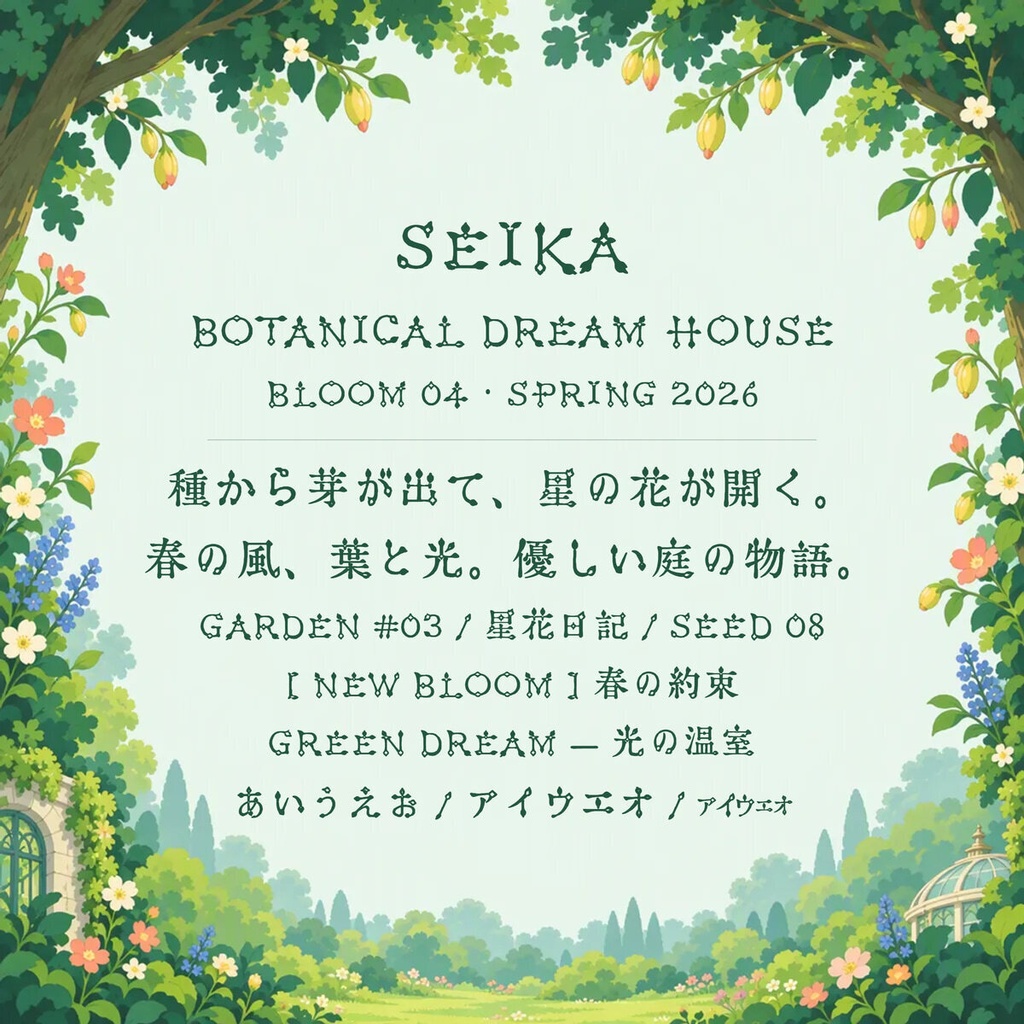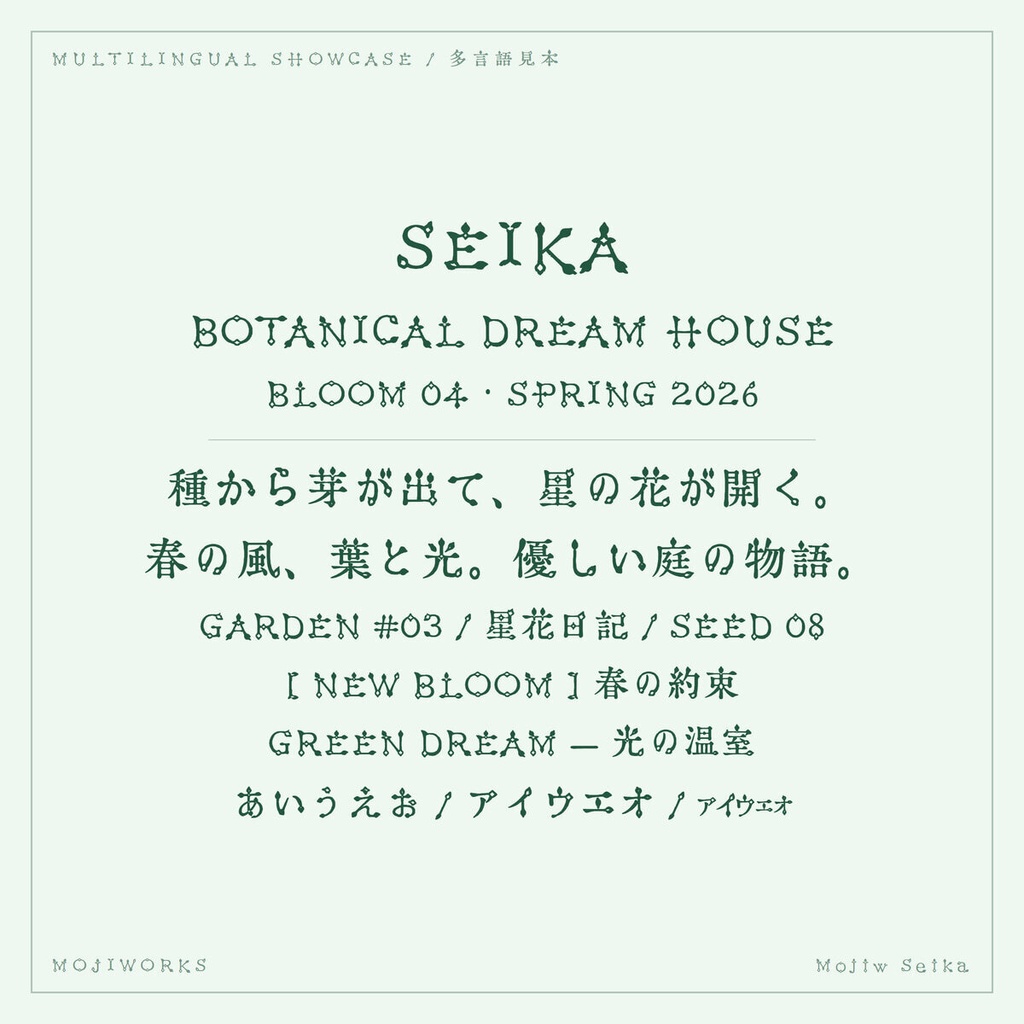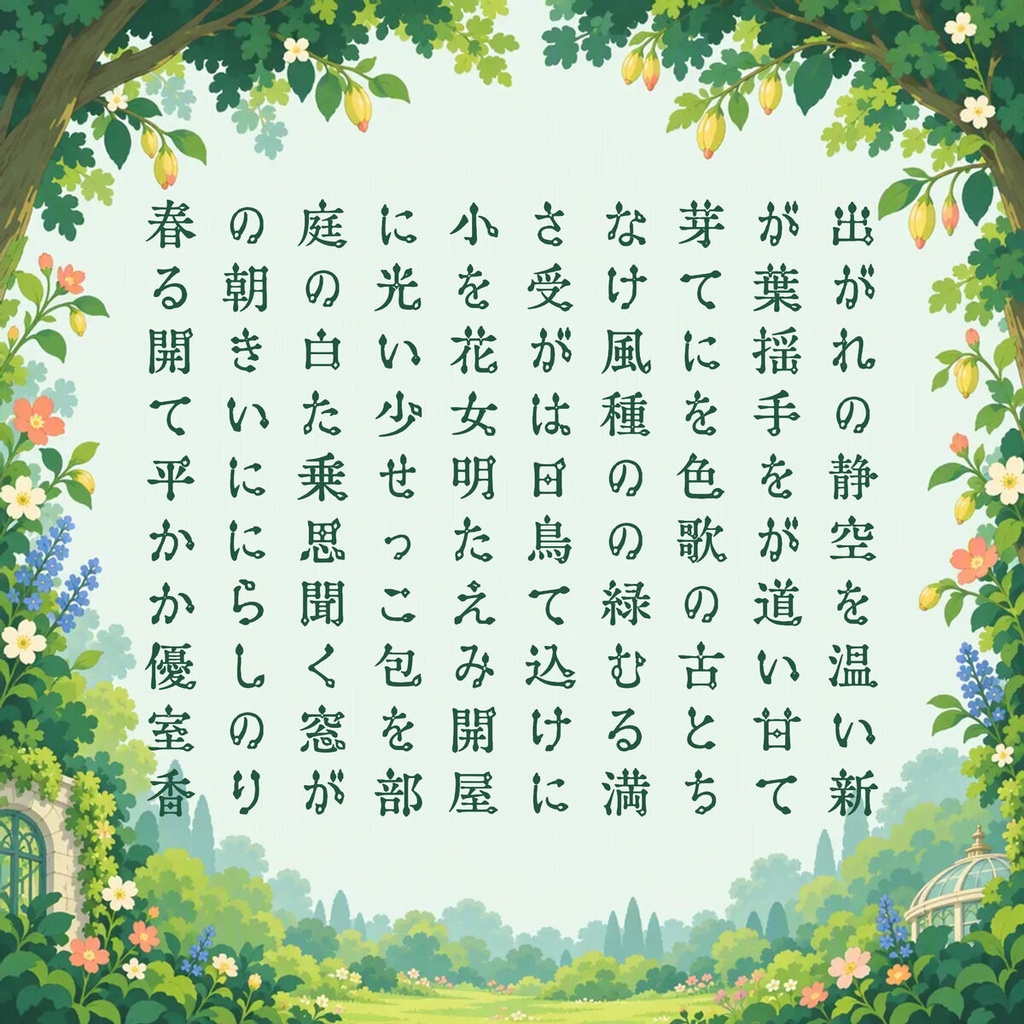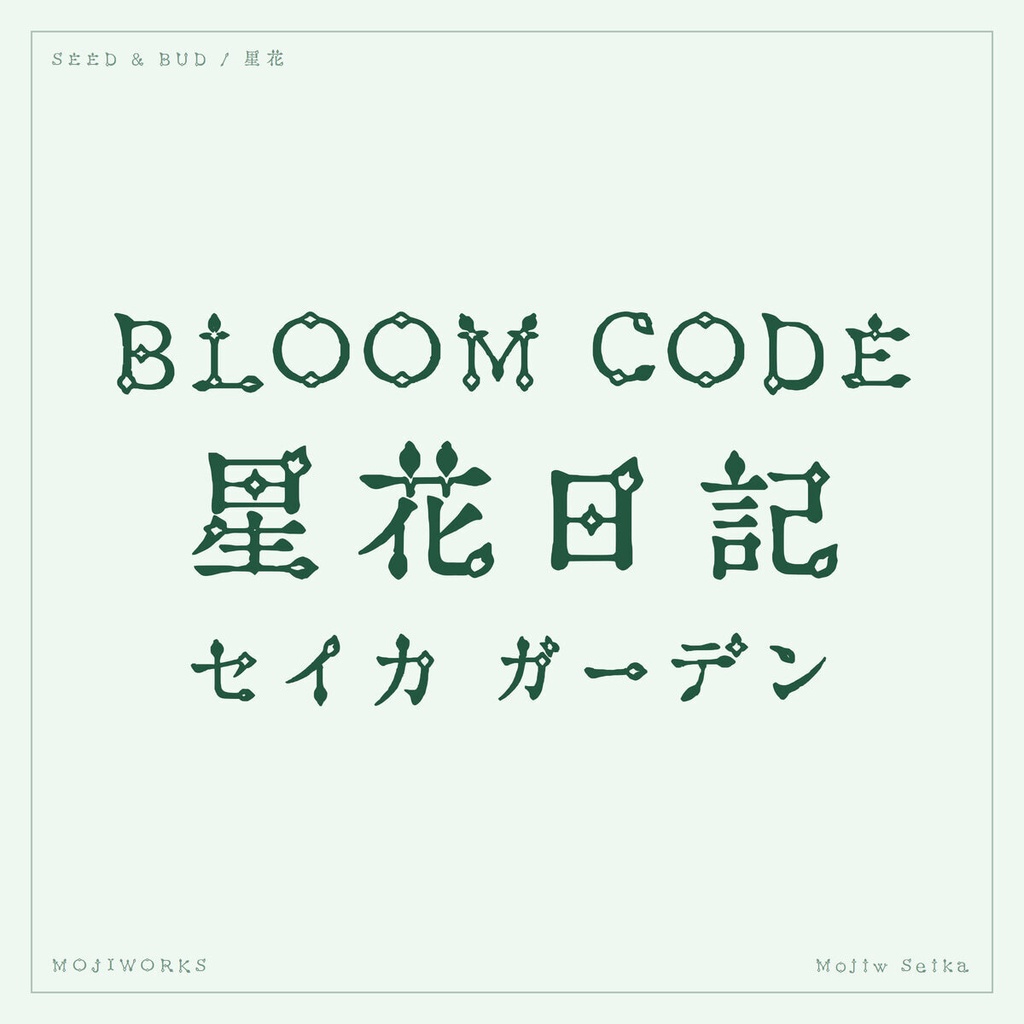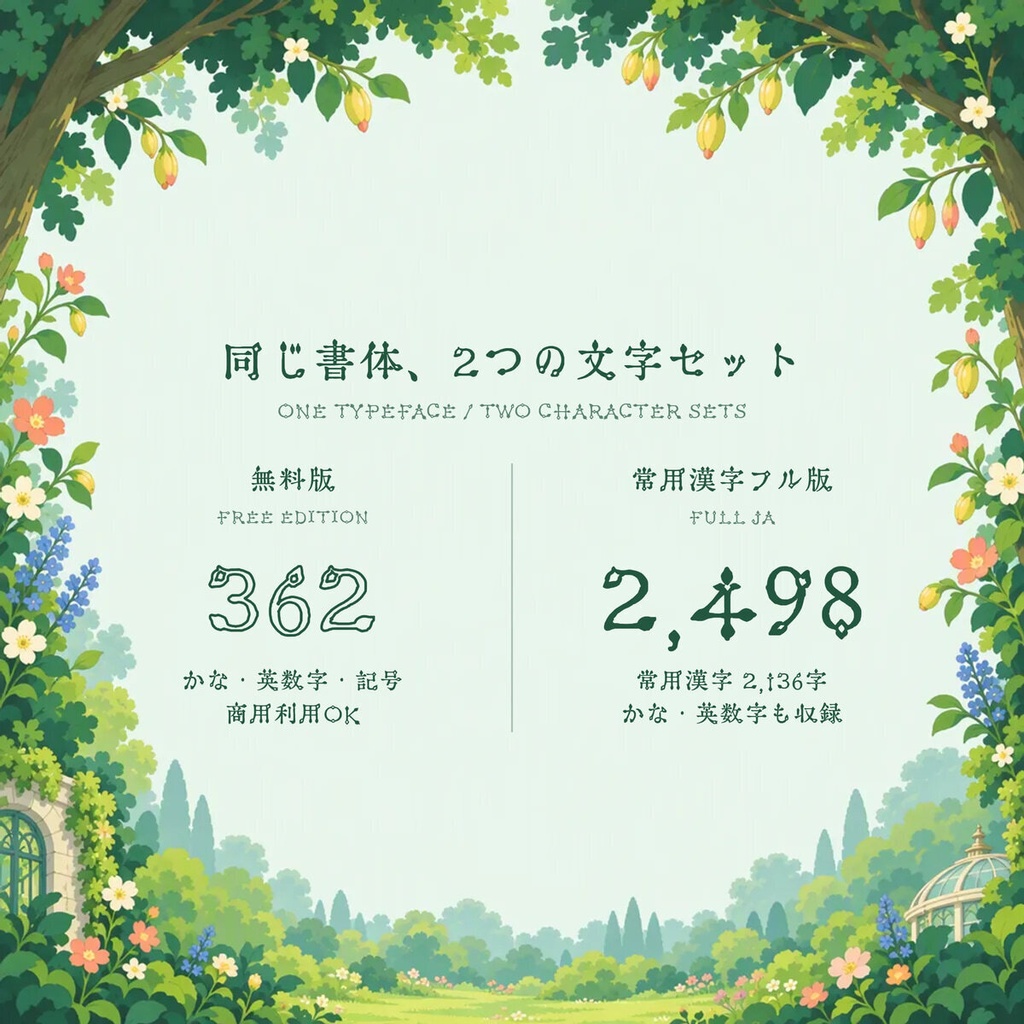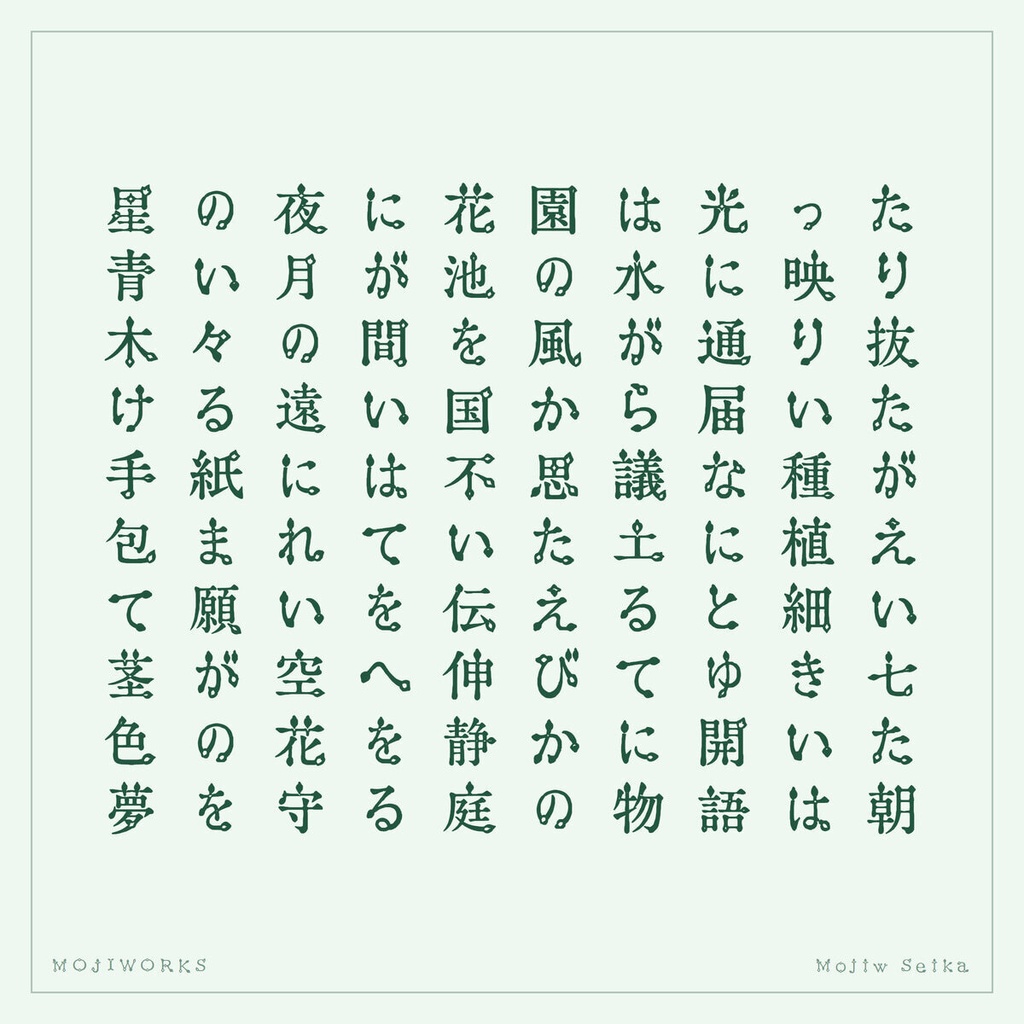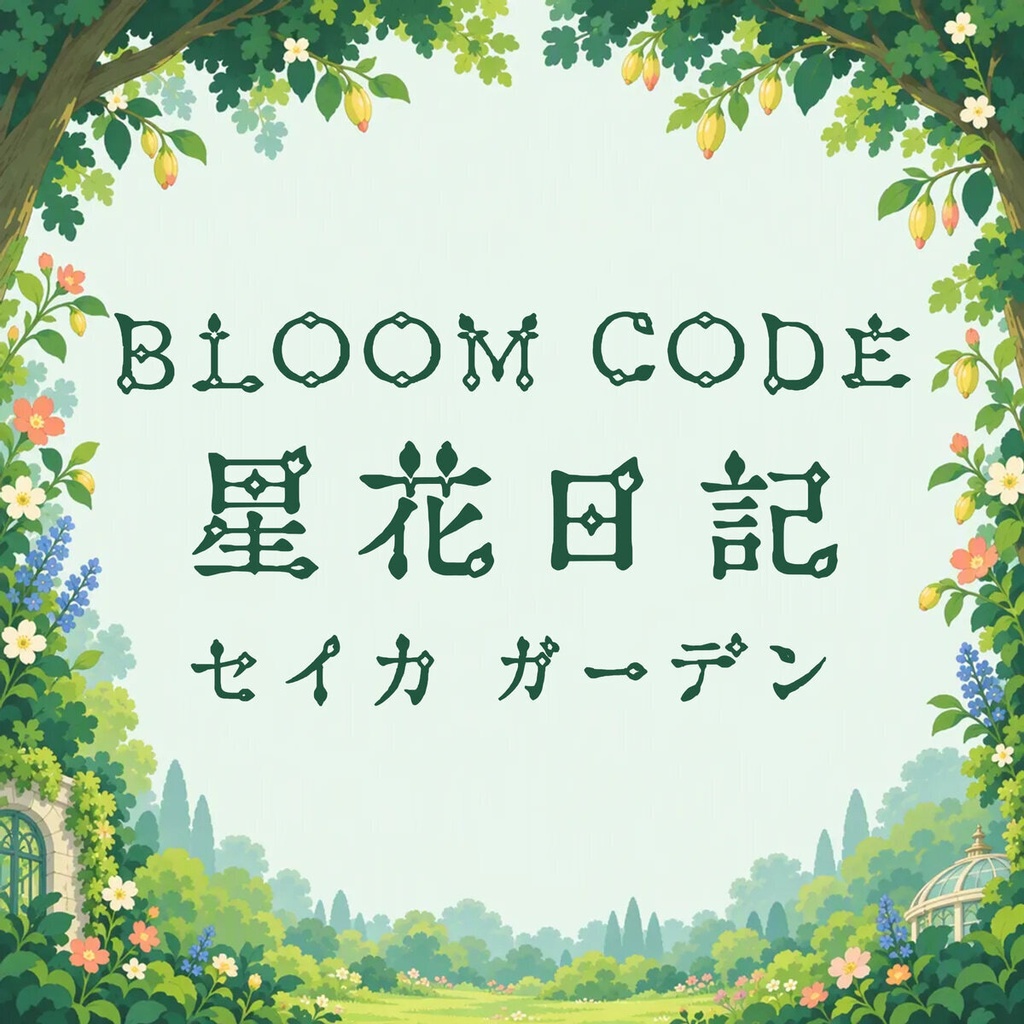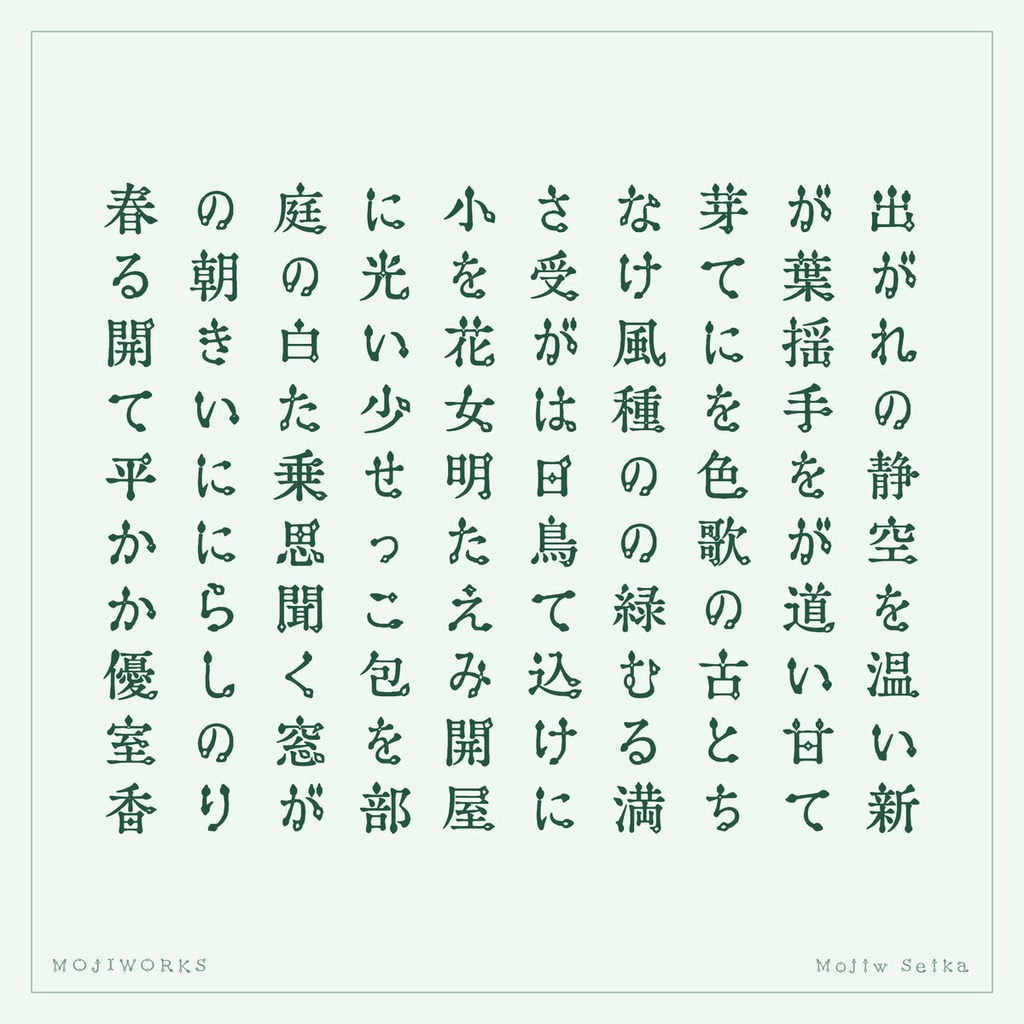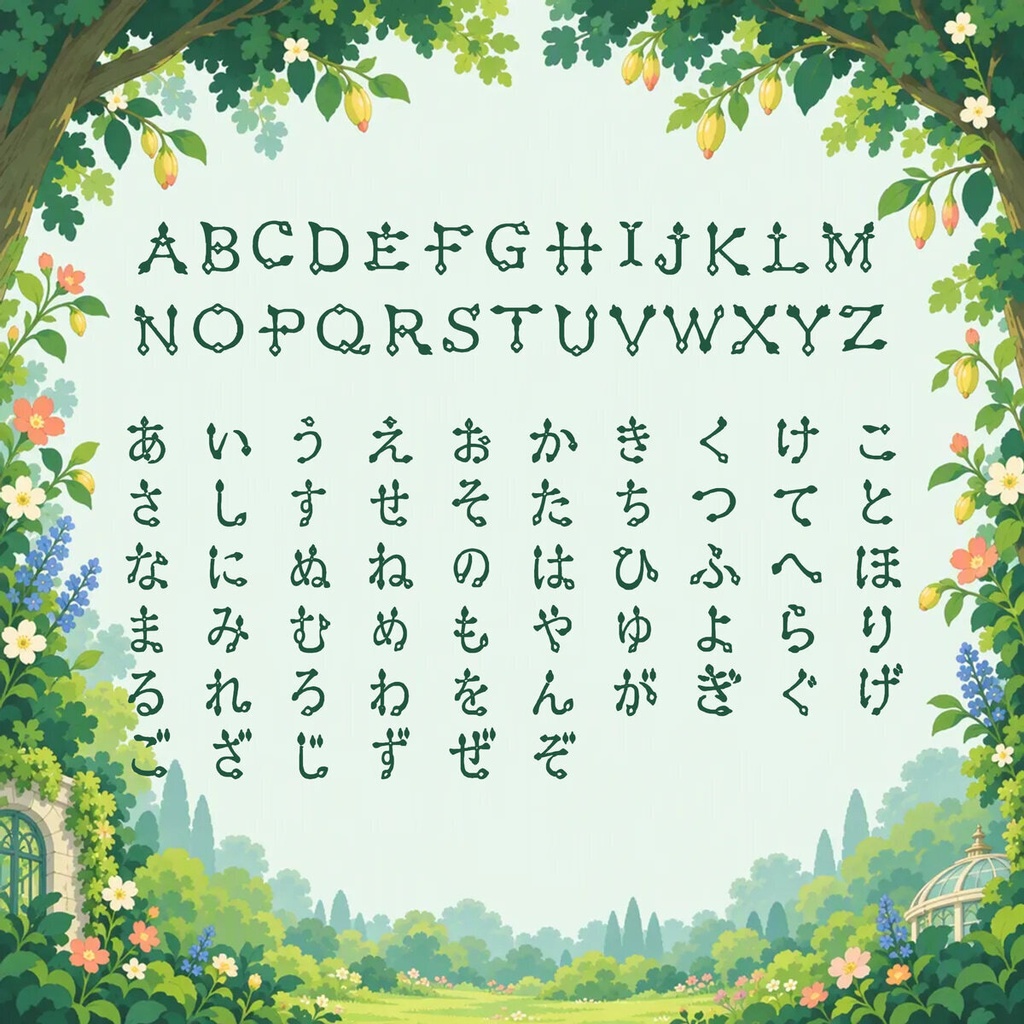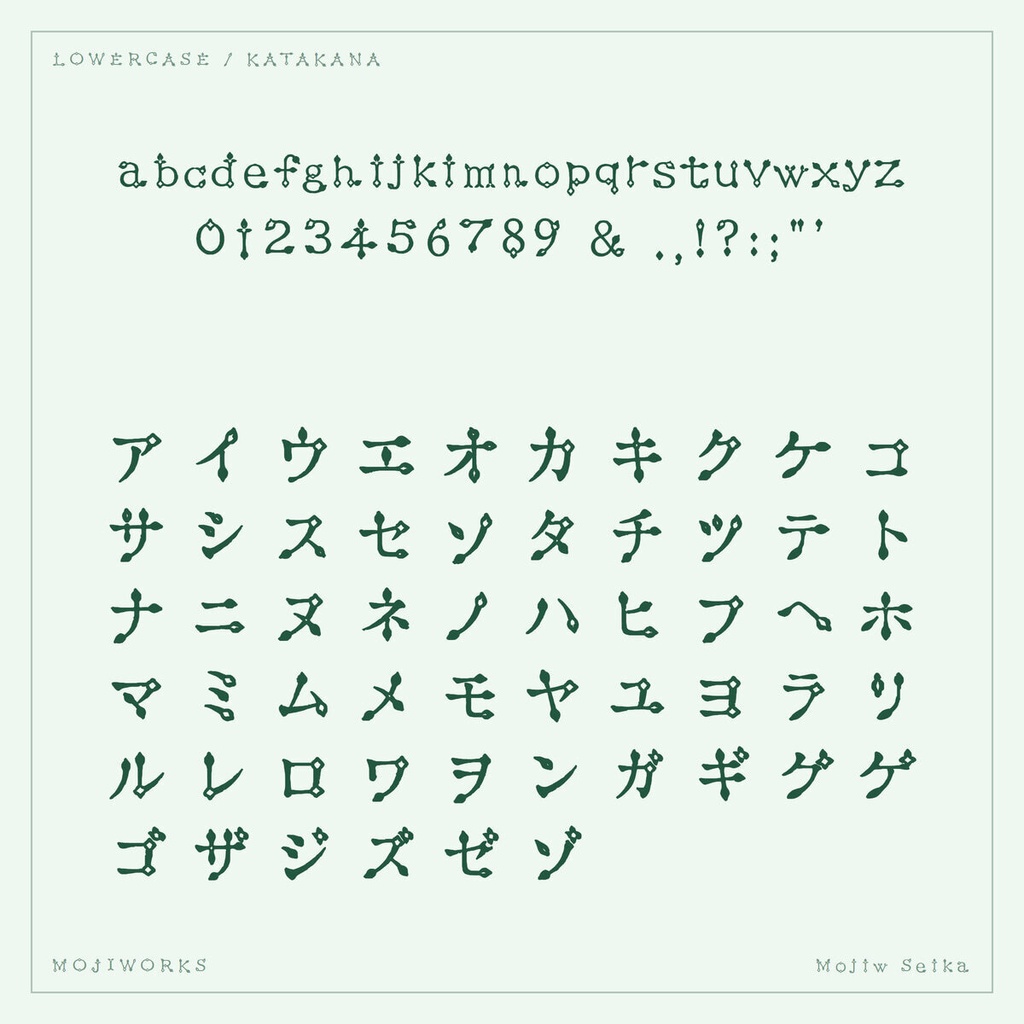
星花 Seika【フォント】 — 芽吹くアールヌーヴォー書体|常用漢字2,136字
種とつぼみが文字の中で芽吹く、優雅な植物装飾書体です。 An elegant botanical display face where seeds and buds grow through every glyph. 【用途 / Use】 コスメ / アイドル / ファンタジー / ロゴ / パッケージ For cosmetics, idols, fantasy projects, logos, and packaging. 【常用漢字フル版 / Joyo Complete】 常用漢字2,136字を完全収録し、ラテン文字・ひらがな・カタカナ・記号を含む全2,437文字を収録しています。半角カナは収録していません。 Includes all 2,136 Joyo kanji and 2,437 characters total, including Latin, hiragana, katakana, and punctuation. Half-width kana are not included. 2437文字 / characters 【関連する収録版 / Other Edition】 ラテン文字・かな・記号を収録したスタンダード版もあります。 The Standard edition includes Latin, kana, and punctuation. ▶ スタンダード版 / Standard: https://mojiworks.booth.pm/items/8826756 【フォント仕様 / Specification】 バージョン / Version: 1.0.1 形式 / Format: TrueType (.ttf), Web (.woff2) 対応環境 / Platform: Windows, macOS, web browsers 収録字一覧 / Character list: CHARSET.txt 同梱 / Included: font files, README, LICENSE, character list, portfolio PDF, product previews. 【利用規約 / License Summary】 個人・商用利用可。1ライセンスは購入者1名に適用されます。 Personal and commercial use is permitted. One license covers one purchaser. 印刷・動画・ロゴ・グッズ等の静的成果物、および購入者が運営するサイトでの同梱WOFF2の利用が可能です。 Static output such as print, video, logos, and merchandise is permitted. The bundled WOFF2 may be used on a website owned or operated by the purchaser. ゲーム・アプリへの組み込みは、利用者が生のフォントを抽出できない形式に限ります。生のフォントを同梱する場合は別途ライセンスをご相談ください。 Game/app embedding requires protection against extraction of the raw font. Contact us for a separate runtime-embedding license when shipping raw font files. 標準ライセンスは1製品・1サイトあたり年間約100,000ユーザーまで。従業員50名超の組織を含む大規模利用は要相談。 Standard coverage is approximately 100,000 users per product/site/year. Larger use and organizations with more than 50 employees require an extended license. フォント本体の再配布・販売・貸与・変換・グリフ抽出・派生フォント制作・生成AI学習やスタイル参照は禁止です。 Redistribution, resale, lending, conversion, glyph extraction, derivative fonts, and generative-AI training or style reference are prohibited. 完全な利用条件は同梱の LICENSE.txt / LICENSE.jp.txt をご確認ください。 The bundled license files are authoritative; consult them for the complete terms. 【ほかのフォント・カスタム制作 / More Fonts and Custom Work】 フォント一覧、オーダーメイド書体、文字追加、拡張ライセンスのご相談はこちら。 Browse our catalog or contact us for custom typefaces, added characters, and extended licenses. https://mojiworks.booth.pm/